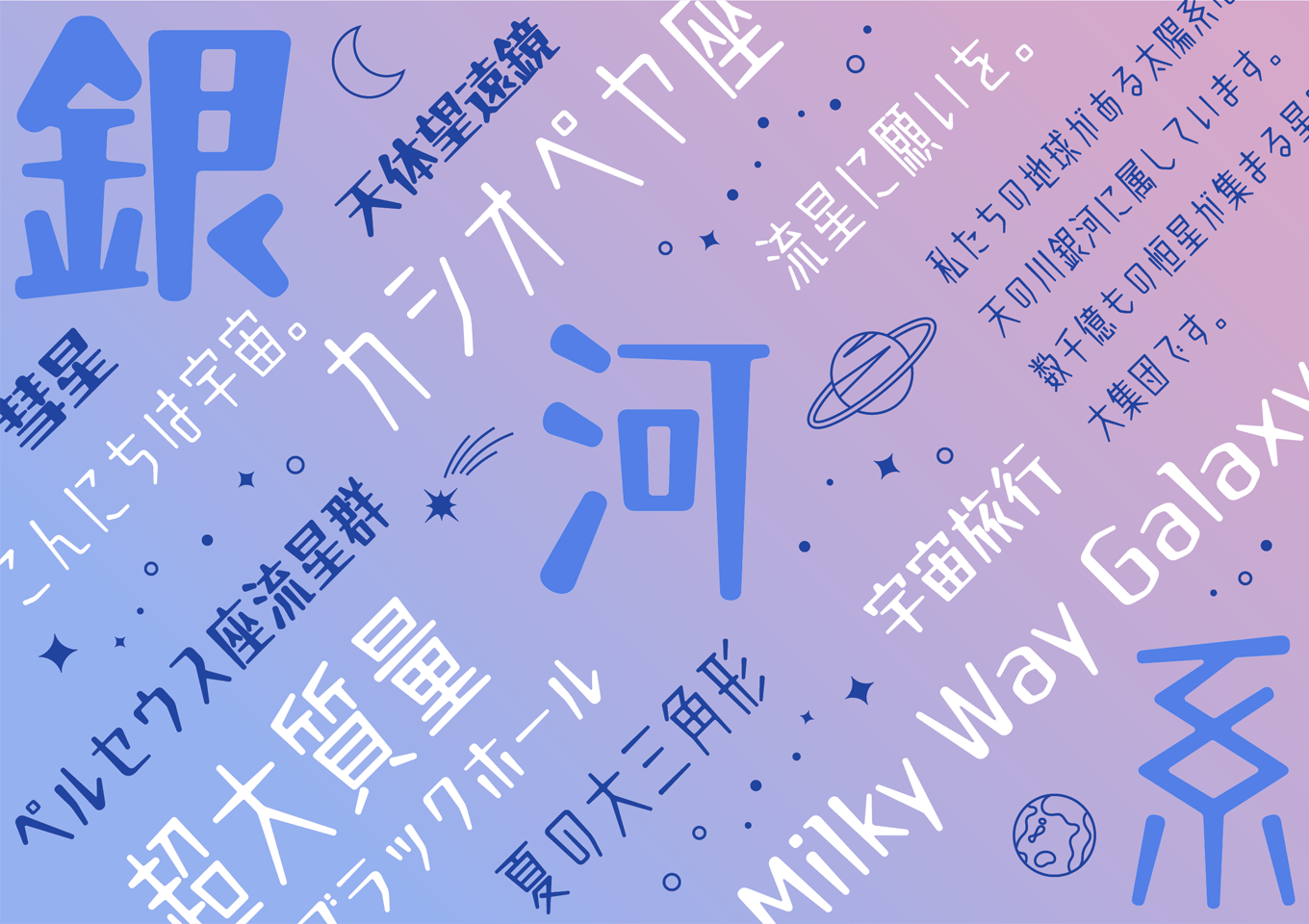
直線のみで構成されたシンプルな設計と、ウエイトごとに異なる字幅が特徴のデザイン書体「ラピスエッジ」を元に開発された丸ゴシック系のデザイン書体です。ラピスエッジのコンセプトを踏襲しつつ先端を丸く処理し、線画の交差部分に墨だまりのような溶けた風合いの処理を施すことで柔らかくポップな印象に仕上げています。
L / M / B
直線のみで構成されたシンプルな設計と、ウエイトごとに異なる字幅が特徴のデザイン書体「ラピスエッジ」を元に開発された丸ゴシック系のデザイン書体です。ラピスエッジのコンセプトを踏襲しつつ先端を丸く処理し、線画の交差部分に墨だまりのような溶けた風合いの処理を施すことで柔らかくポップな印象に仕上げています。
L / M / B